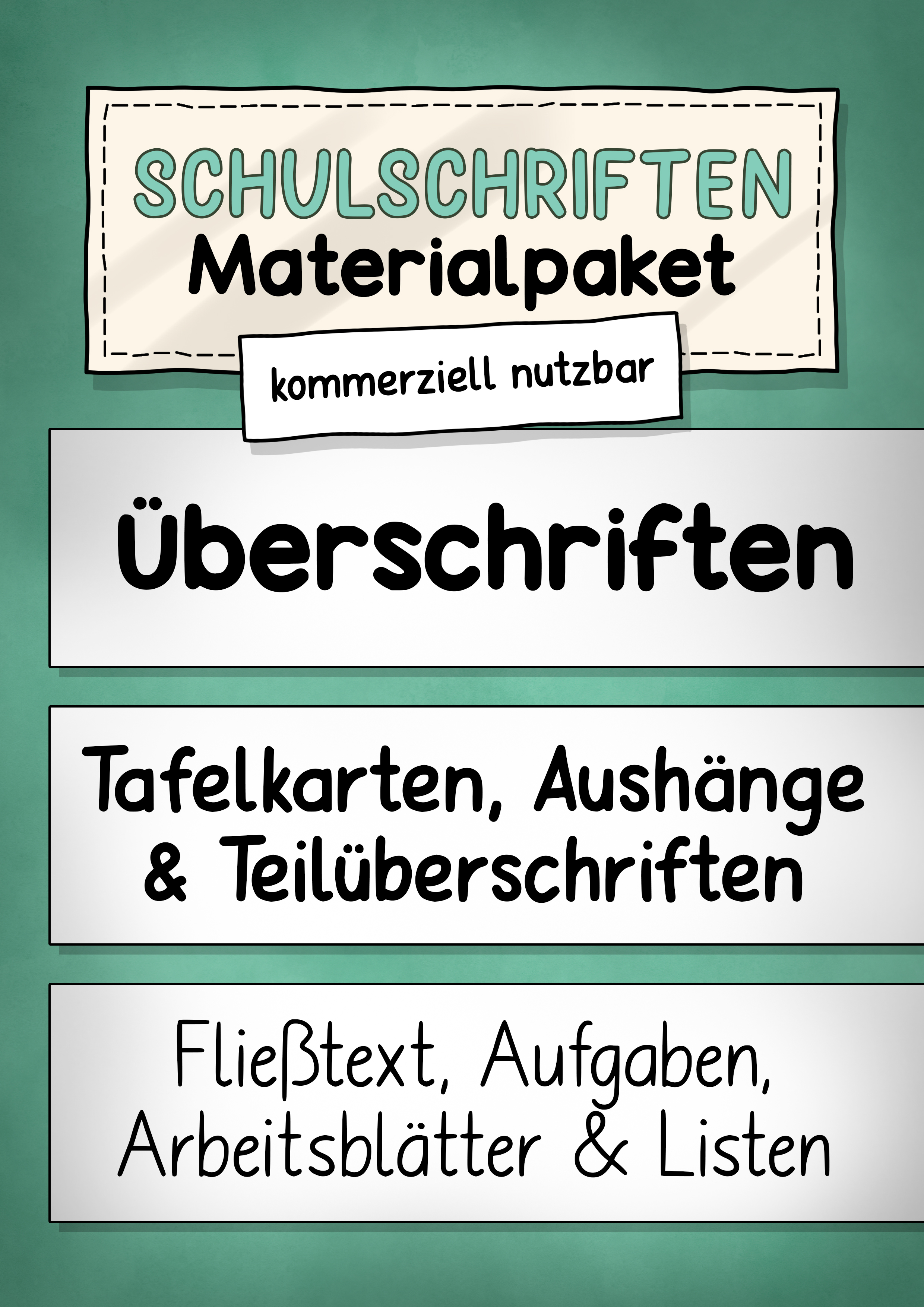
"MeisterMiezimus" ist eine Schulschrift, die privat und im Bildungsbereich auch kommerziell genutzt werden darf. Das heißt, du darfst die Schriftart für das Erstellen von Unterrichts-/Schulmaterial verwenden, das du später verkaufen möchtest. Verlinke dabei immer meine eduki-Seite und gib meinen Profilnamen an.Du bekommst die Schriftart in den gängigen zwei Formaten für alle Windows-/iOS-/Linux-Nutzer: .ttf und .otf. Die Dateien sind in einer .zip-Datei gepackt. In der beiliegenden .pdf befindet sich eine Anleitung zum Entpacken und Installieren.Die Schrift selbst enthält über 170 Glyphen. Sollten dir bestimmte Glyphen fehlen, schreibe es mir als Kommentar.Viel Freude mit der MeisterMiezimus-Schriftart!
"Krallenkaiser" ist eine super Schrift für Überschriften oder immer dann, wenn man dicke Buchstaben braucht.Die Schulschrift darfst du im Bildungsbereich auch kommerziell nutzen. Verlinke dabei immer meine eduki-Seite und gib meinen Profilnamen an.Du bekommst die Schriftart in den gängigen zwei Formaten für alle Windows-/iOS-/Linux-Nutzer: .ttf und .otf. Die Dateien sind in einer .zip-Datei gepackt. In der beiliegenden .pdf befindet sich eine Anleitung zum Entpacken und Installieren.Viel Freude mit der Krallenkaiser-Schriftart!
"Mauzarella" ist eine Schulschrift, die privat und im Bildungsbereich auch kommerziell genutzt werden darf. Das heißt, du darfst die Schriftart für das Erstellen von Unterrichts-/Schulmaterial verwenden, das du später verkaufen möchtest. Verlinke dabei immer meine eduki-Seite und gib meinen Profilnamen an.Du bekommst die Schriftart in den gängigen zwei Formaten für alle Windows-/iOS-/Linux-Nutzer: .ttf und .otf. Die Dateien sind in einer .zip-Datei gepackt. In der beiliegenden .pdf befindet sich eine Anleitung zum Entpacken und Installieren. Die Schrift selbst enthält über 170 Glyphen. Sollten dir bestimmte Glyphen fehlen, schreibe es mir als Kommentar.Viel Freude mit der Mauzarella-Schriftart!